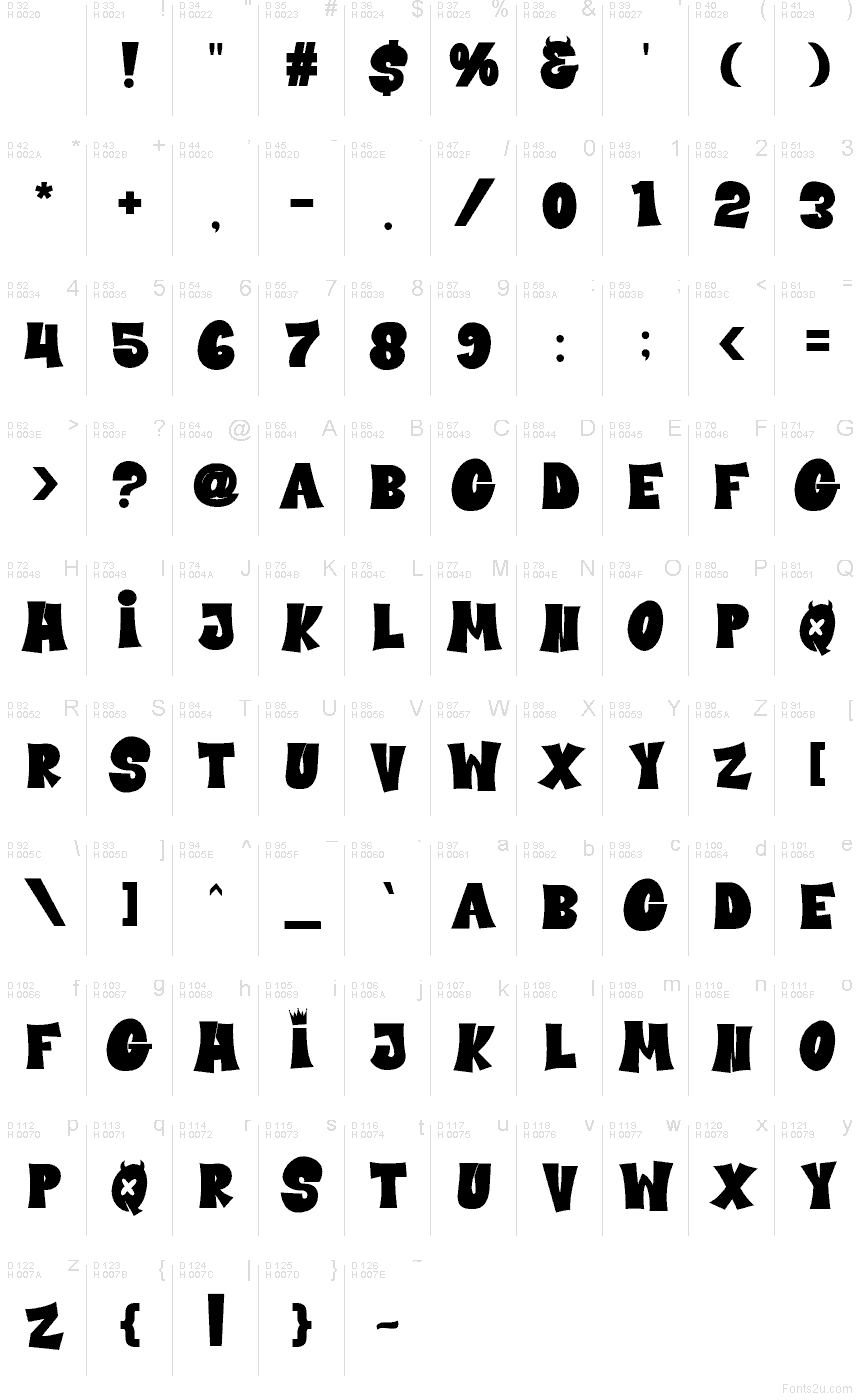
King Jack Style par CikareotypeStudio est une police d'affichage gratuite de style cartoon, dotée d'une personnalité haute en couleur tout droit sortie d'un livre d'histoires. Les lettres penchent et tanguent avec leurs silhouettes épaisses et irrégulières, mêlant traits épais et courbes découpées, tandis que le « I » couronné donne à l'ensemble un côté espiègle, digne d'un roi le temps d'une journée.
Elle est idéale pour les titres d'affiches, les flyers d'événements pour enfants, les jeux vidéo, les emballages de snacks et toute identité visuelle nécessitant une voix forte et malicieuse. Utilisez-la pour vos titres ou logos, car les majuscules semblent déjà prendre vie sur scène plutôt que de se comporter comme de simples lettres.